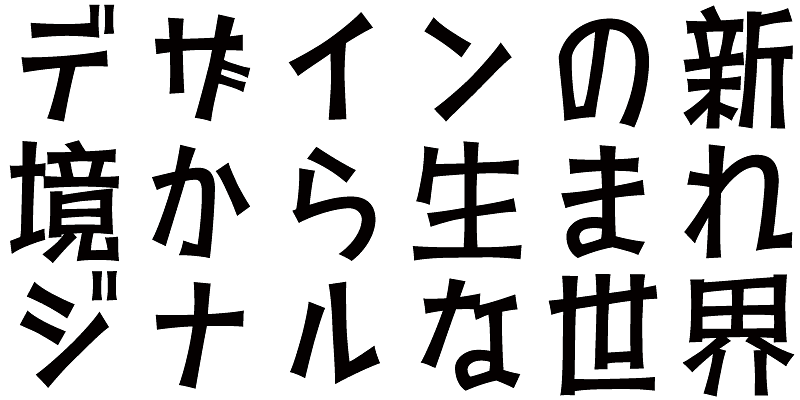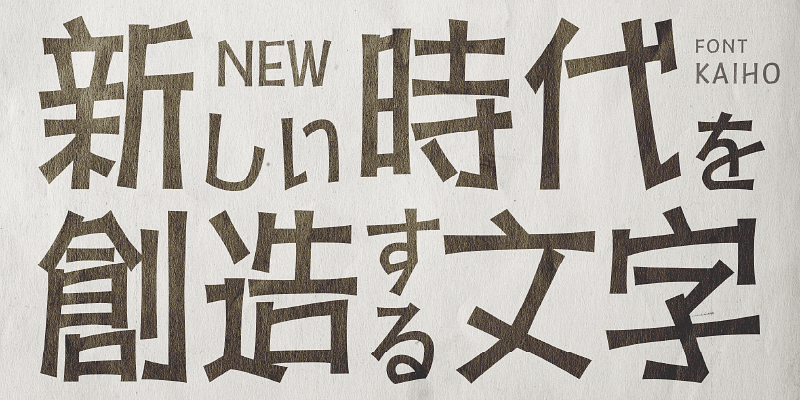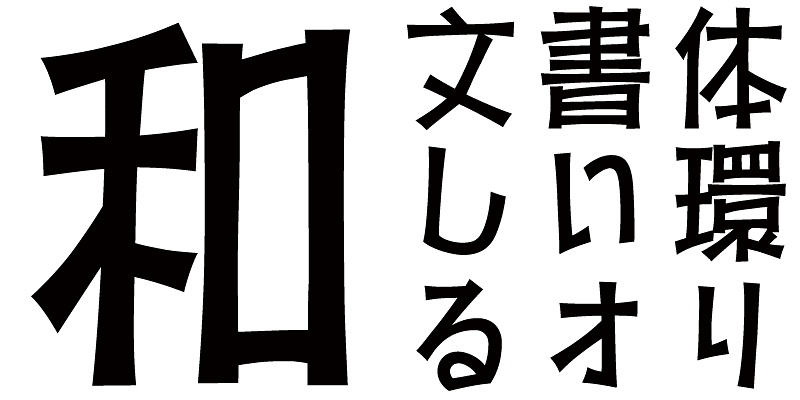
Das Design basiert auf dem Schriftzug, der auf politischen Plakaten der Studentenproteste in den 1960er Jahren verwendet wurde. Diese Schrift erinnert an diese Ära und eignet sich gut für die Gestaltung von Titeln mit nostalgischen Botschaften.
In der heutigen japanischen Schriftproduktion gelten die 7.000 Zeichen des JIS-Standards als unabdingbar. Aber brauchen alle Schriften wirklich 7.000 Zeichen? Im Zeitalter des Fotosatzes wurden weit weniger Zeichen benötigt. FONT1000, eine Gruppe unabhängiger Schriftdesigner, ging von dieser einfachen Frage aus. Wir haben die mindestens 1.000 (ideografischen) Kanji-Zeichen ausgewählt, die für den Satz in Japanisch erforderlich sind, und aktiv Schriften und Schriftbilder dafür entworfen. Dieser 1000-Kanji-Zeichensatz wurde unter Verwendung von Zeichenhäufigkeitsdaten ausgewählt, die u. a. von Zeitungsunternehmen, Verlagen und Sprachforschungsinstituten zusammengestellt wurden, und enthält auch Kana-Silbenzeichen und Satzzeichen. FONT1000 begann 2001 mit 25 Designern und 25 Schriften. Heute haben wir 130 Schriften und sind auf fast 40 Mitglieder angewachsen, sodass wir an Schriften mit mehr Zeichen arbeiten können.